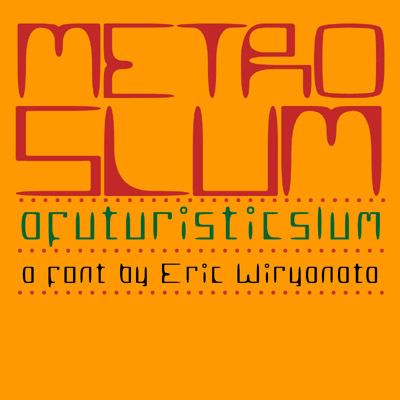
Metro Slum di Eric Wiryanata è un font display gratuito e futuristico dall'elegante atmosfera retro-urbana. Le lettere accostano rettangoli alti e arrotondati a curve strette e punte a goccia, dando al design un ritmo techno morbido che richiama sia la fantascienza che il tardo Art Nouveau.
Funziona benissimo per poster musicali, flyer per eventi, titoli di giochi indie, copertine di moda e branding essenziale, dove il font gratuito deve comunicare in poche lettere. Usalo per loghi, monogrammi o titoli di apertura quando cerchi una silhouette stretta e stilizzata, e quegli inusuali bagliori superiori e inferiori per dare il tono giusto.